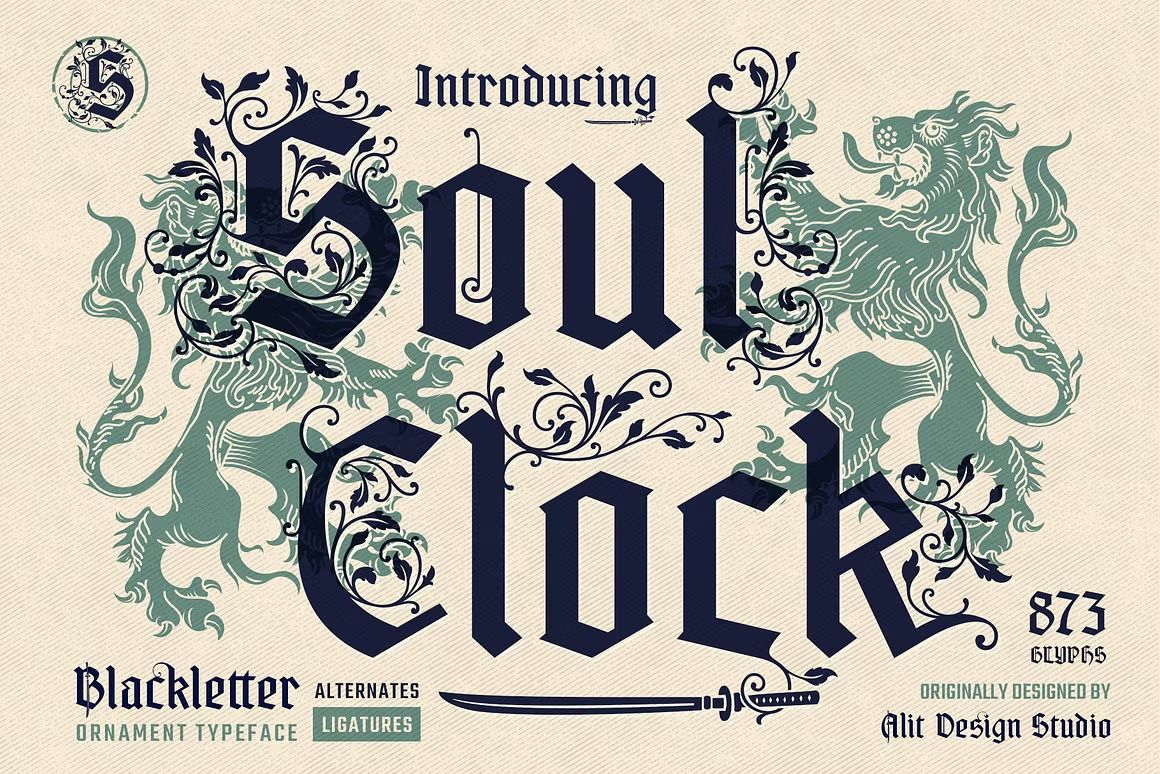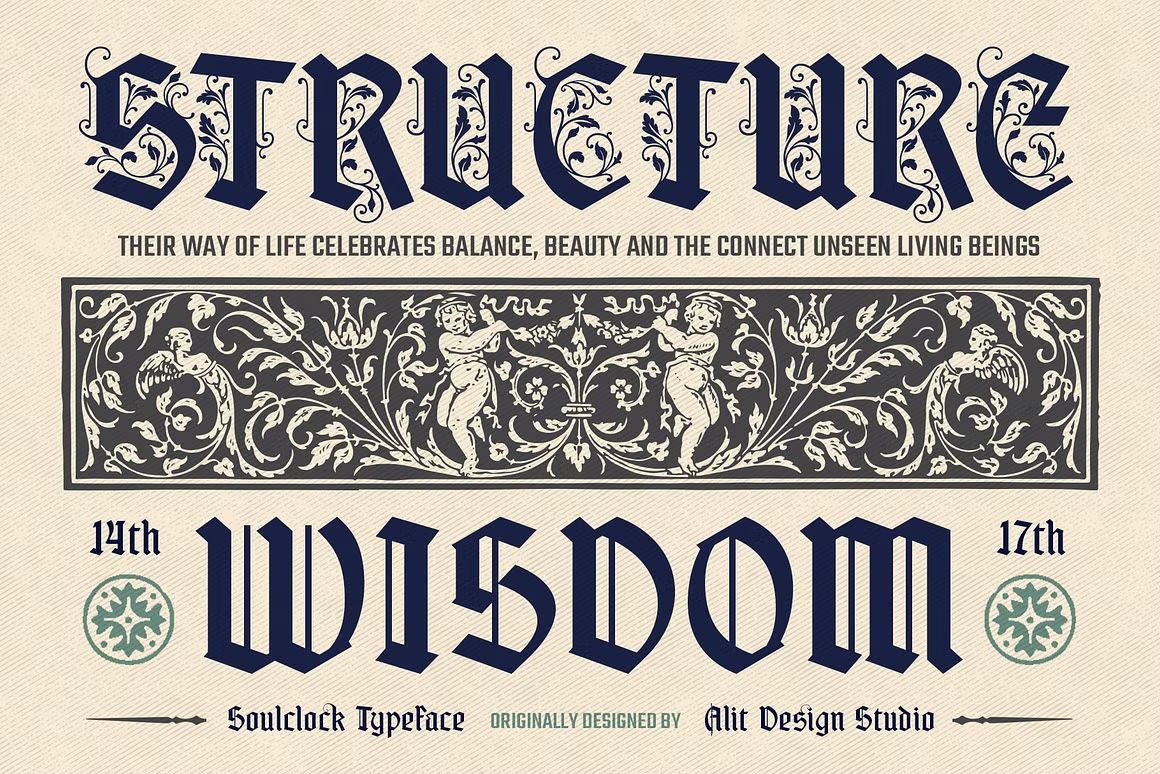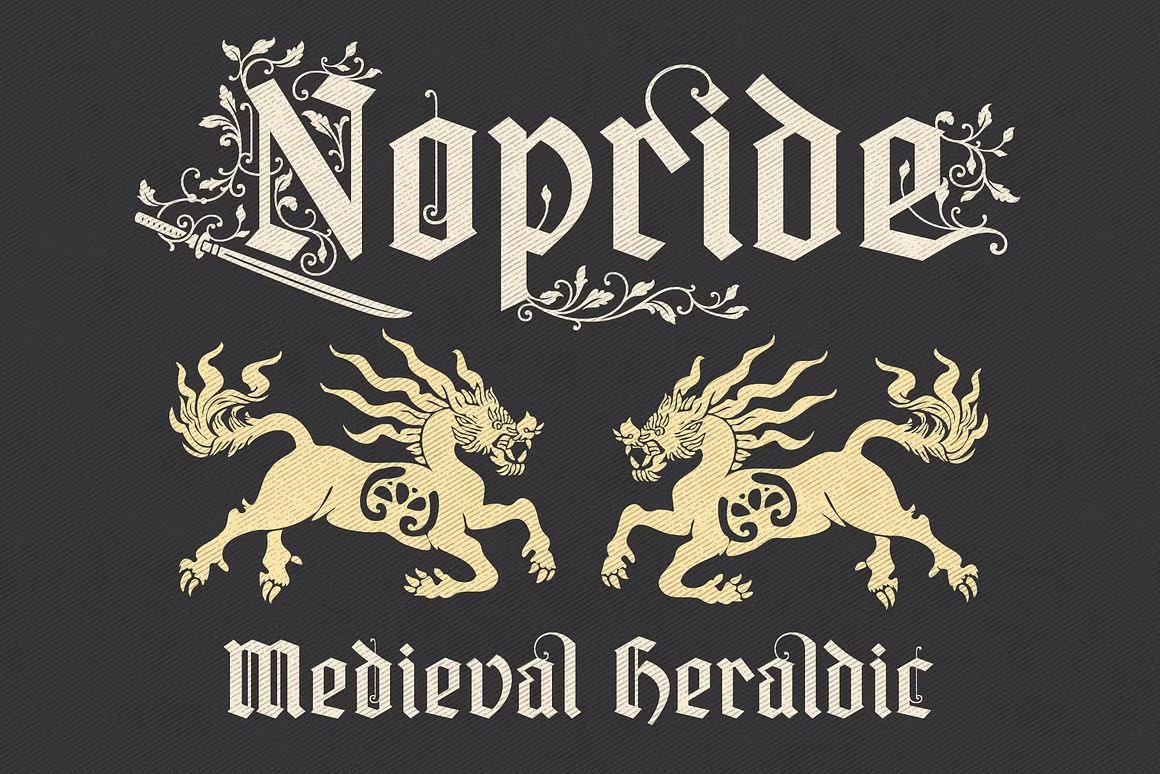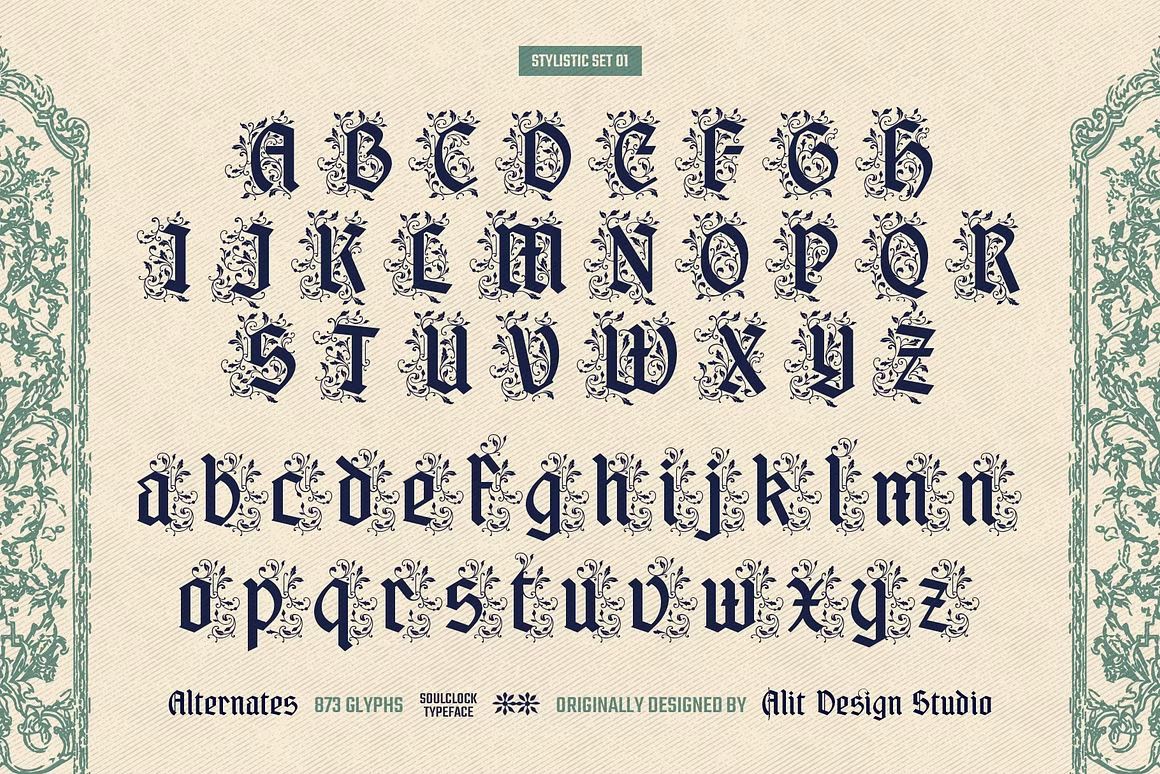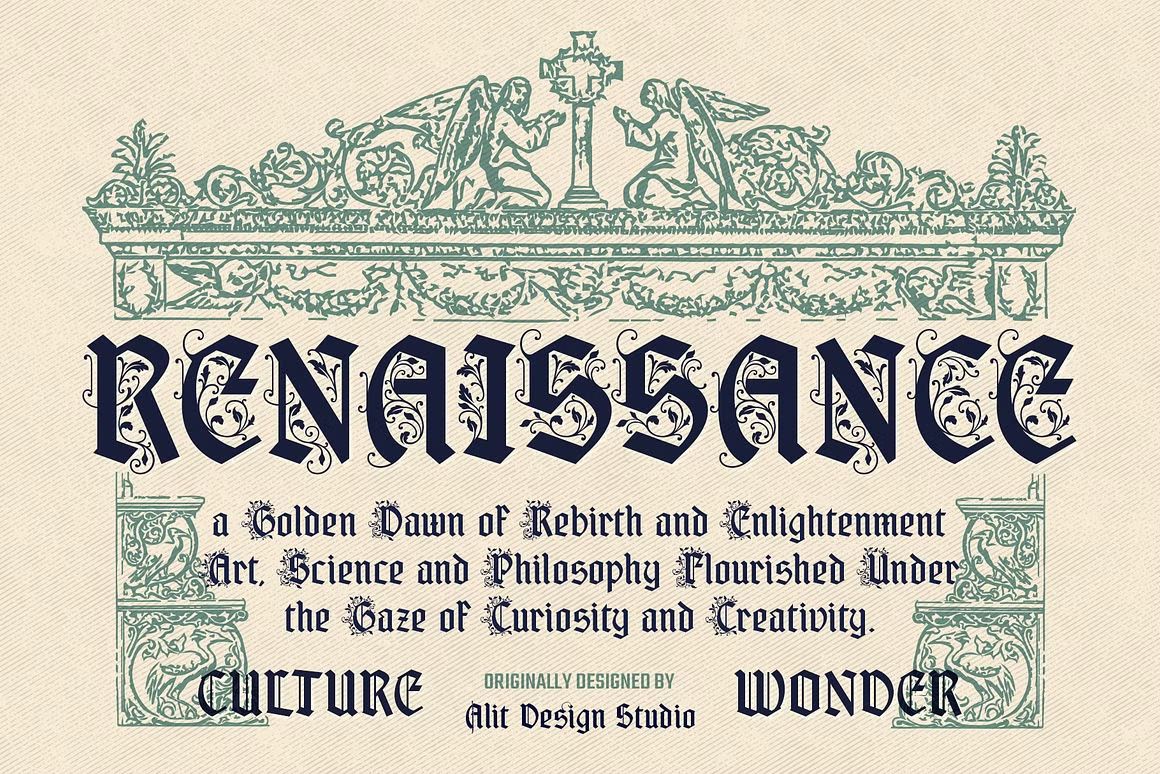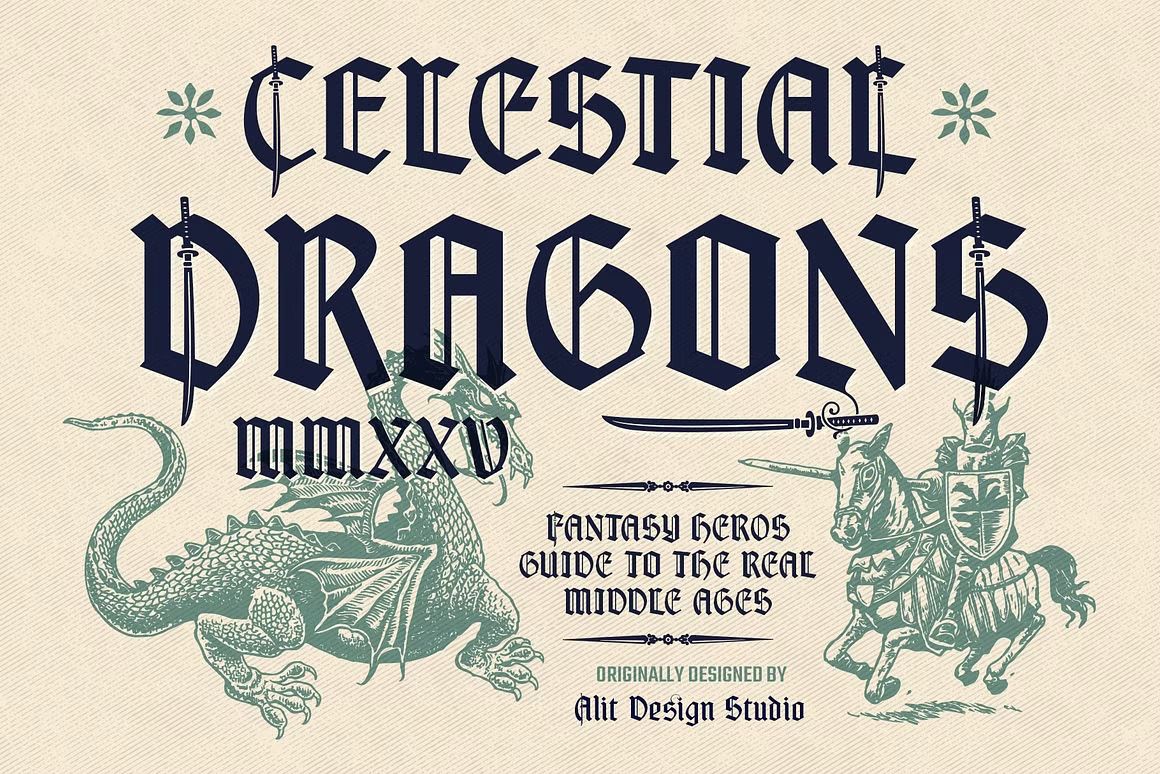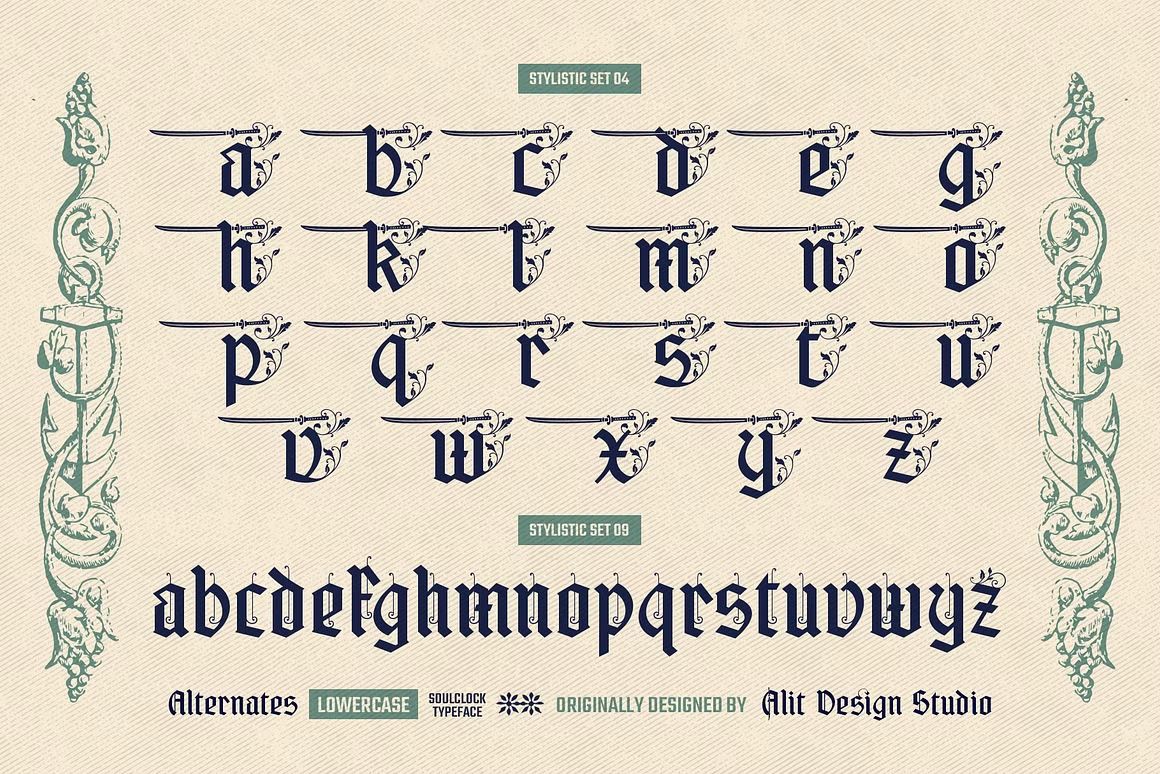
Soul Clock Typeface – Blackletter Font
Soul Clock adalah font blackletter bergaya gothic-modern yang kuat dan penuh karakter. Cocok untuk desain vintage, musik, dan tattoo. Format OTF/TTF/WOFF, siap digunakan.
Soul Clock adalah font blackletter yang memadukan gaya gothic klasik dengan sentuhan modern dan berani. Dengan bentuk huruf tajam, tegas, dan penuh ornamen, font ini cocok untuk desain bertema vintage, tattoo, musik metal, poster, apparel, dan branding yang ingin tampil dramatis dan penuh karakter. Soul Clock memberikan kesan misterius, kuat, dan artistik dalam setiap aplikasi desain.
• Gaya blackletter klasik dengan elemen modern
• Ideal untuk desain gothic, poster, logo musik, dan tattoo
• Termasuk huruf besar, kecil, angka, simbol, dan ligatur